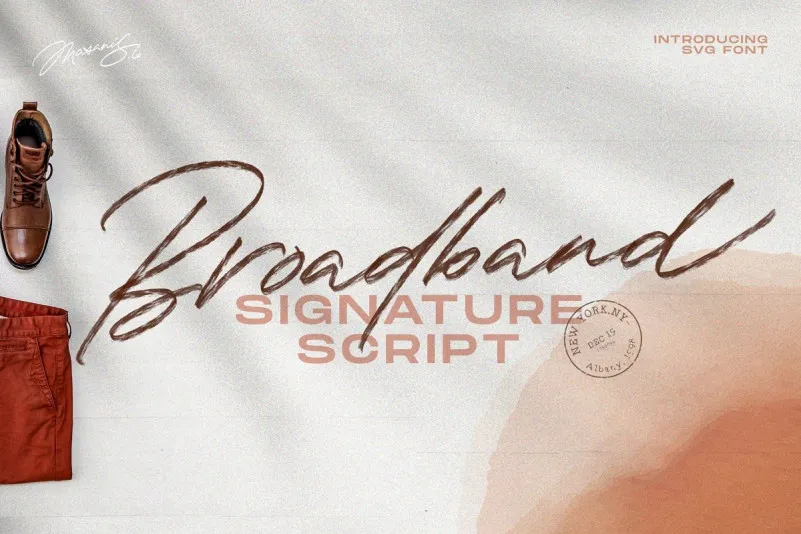
Através do The Broadband Script Font, você pode adicionar um toque pessoal a qualquer projeto sem comprometer sua personalidade ou estilo. Esta fonte script é perfeitamente adaptada para branding pessoal, criando uma conexão emocional que não se resume ao texto impresso. Ela também é adequada para design de móveis de casa e embalagens de produtos. Com traços rápidos e um estilo personalizado, o The Broadband Script oferece uma solução perfeita para estilos de texto que complementam qualquer imagem de fundo. Este recurso gráfico, desenvolvido pela 24Design, é ideal tanto para quem busca personalidade em sua marca quanto para aqueles que desejam dar um toque diferente a seus projetos digitais ou impressos. Seja você criando uma identidade visual única, criando embalagens de produtos ou até mesmo adicionando um texto ao fundo de uma imagem, The Broadband Script tem tudo o que precisa para agregar valor à sua criação.